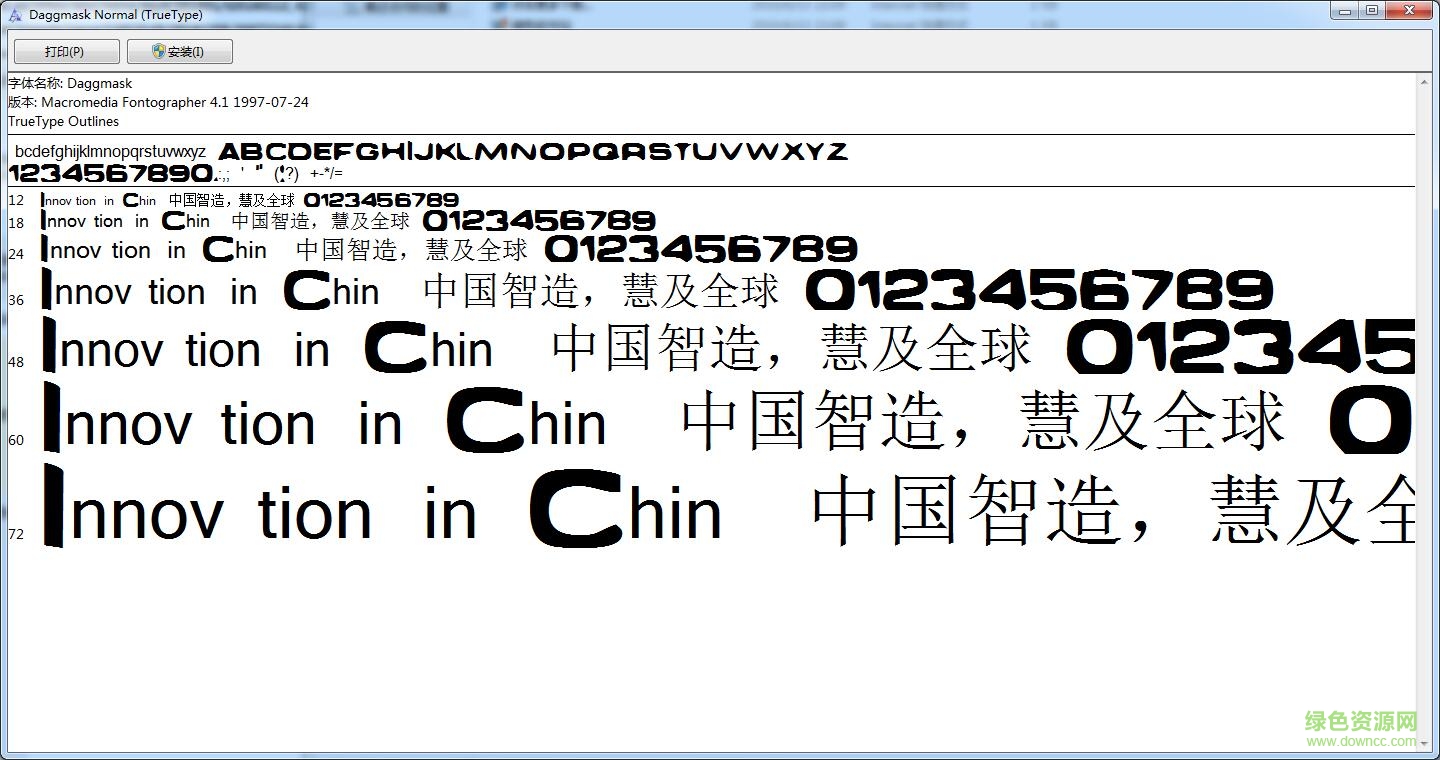
Daggmask英文字體是一種免費(fèi)的英文格式字體應(yīng)用。這款字體看起來(lái)有些滑稽,但是實(shí)際使用的時(shí)候是有活躍氣氛的功能的,而且還是非常的方便,可以在排版設(shè)計(jì)的時(shí)候輸入英文使用!歡迎大家來(lái)綠色資源網(wǎng)下載。